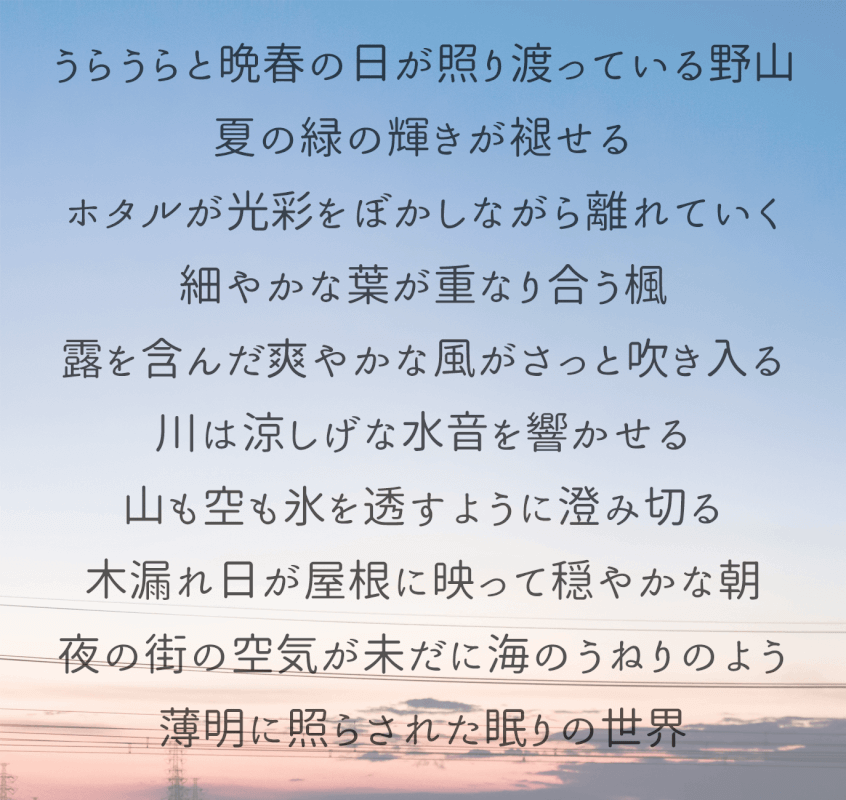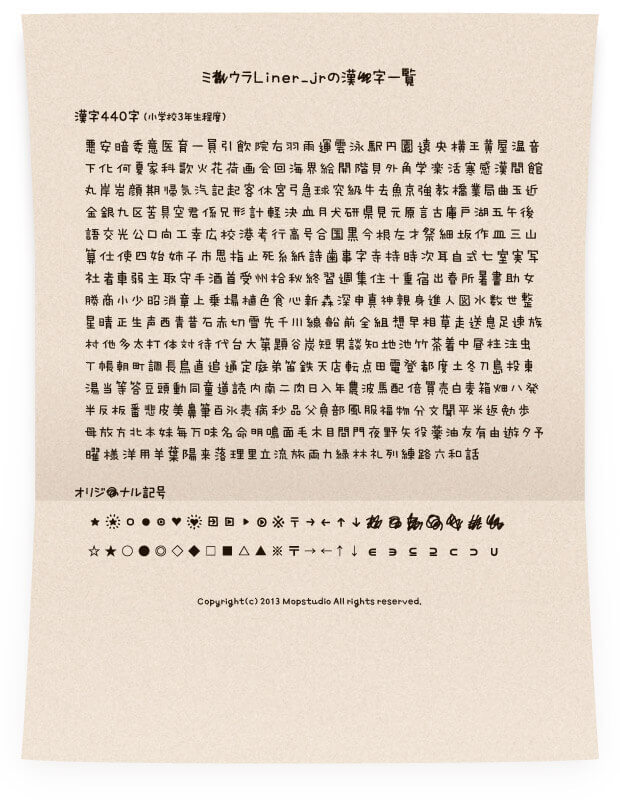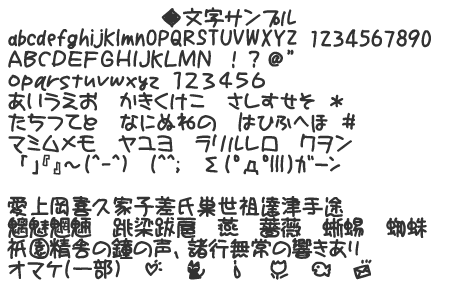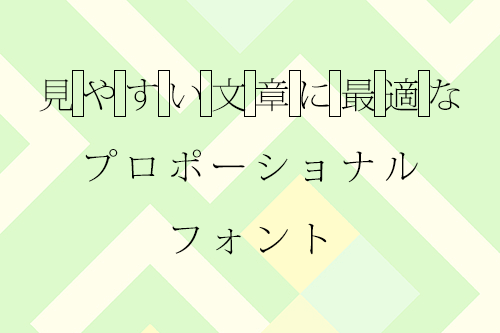
見やすい文章に最適なプロポーショナルフォント23選
文字ごとに文字幅が異なるフォントをプロポーショナルフォント(可変幅フォント)と言います。今回は、文章に最適なプロポーショナルフォントを23選まとめました。長めの文章を見せたい時にプロポーショナルフォントを使用すればバランスがとれたデザインとなるでしょう。
CHUBBY
カクカクとしたプロポーショナルフォント。大文字で打つと黒塗り、小文字で打つと白抜きの文字が表示されます。
IPA Pゴシック
「JIS X 0213:2004」をサポートし、商用・非商用に限らず無償で利用できる高品位な日本語フォントのゴシック体。
IPA P明朝
「JIS X 0213:2004」をサポートし、商用・非商用に限らず無償で利用できる高品位な日本語フォントの明朝体。
kawaii手書き文字
ちょっぴりクセのある可愛い手書きペン字をひとつひとつフォント化したもの。漢字は常用漢字を中心に約1,930字を収録。
MTたれっぴ
落書き調のユニークなプロポーショナルフォント。漢字は第一水準漢字、第二水準漢字のすべてを収録。
S2GPうにフォント
手書き文字から作成されたプロポーショナルフォント。
S2GPつきフォント
手書き文字から作成されたプロポーショナルフォント。
S2GP殴り書き
手書き文字から作成されたプロポーショナルフォント。
S2GP海フォント
手書き文字から作成されたプロポーショナルフォント。
S2GP月フォント
手書き文字から作成されたプロポーショナルフォント。
VL Pゴシック
M+ アウトラインフォントベースのモダンゴシック体の日本語 TrueType フォント。
あくあPフォント
JIS第一・第二水準の漢字に対応した手書きのTrueTypeフォント。
あずきフォントP
「マジメすぎず、可愛すぎないフォント」をイメージした手書きフォント。
あんずもじ始
教科書体を参考した手書き風フォント。小学校6年間で習う教育漢字1006文字を収録しています。
あんずもじ始等幅
上記の「あんずもじ始」の等幅フォント版。
あんずもじ奏
絵文字の変わりに音符を収録したプロポーシャルフォント。
あんずもじ湛